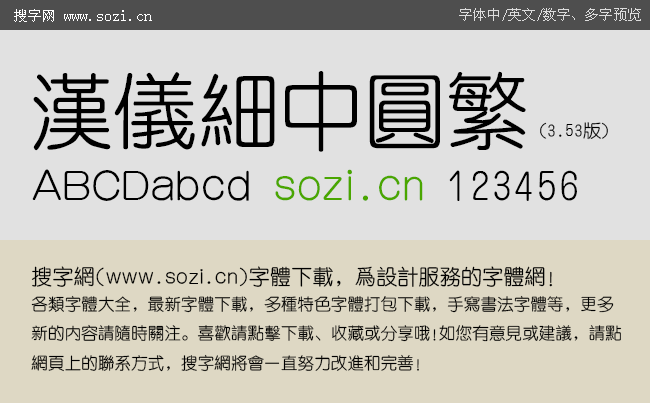
漢儀細(xì)中圓繁
搜字網(wǎng)提供一款漢儀細(xì)中圓繁字體下載,該字體每個(gè)漢字都經(jīng)過(guò)精心設(shè)計(jì),筆畫(huà)粗細(xì)均勻、結(jié)構(gòu)美觀。每個(gè)字的圓角、圓頭、勾形都極光潔、風(fēng)格統(tǒng)一,字形放大不變形,縮小顯示清晰,適用于樣本畫(huà)冊(cè),報(bào)紙排版,網(wǎng)頁(yè)標(biāo)題等廣告設(shè)計(jì)應(yīng)用。